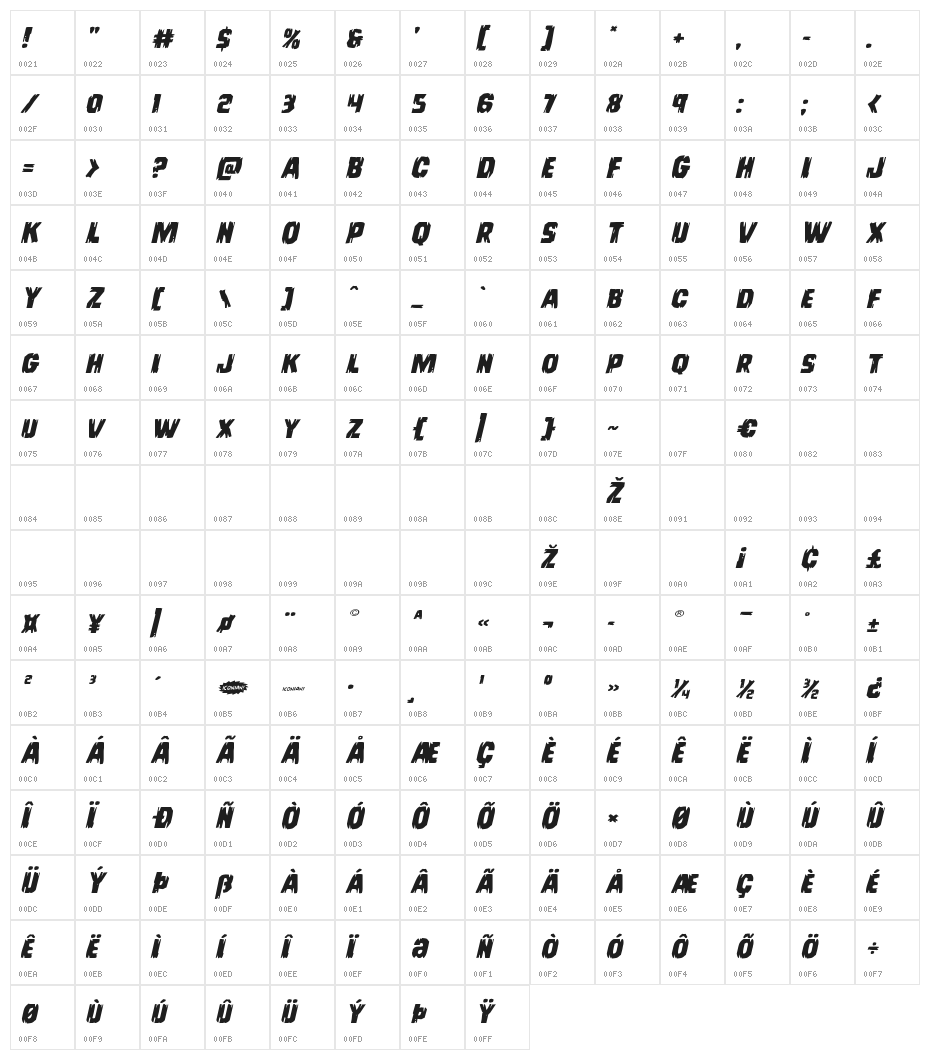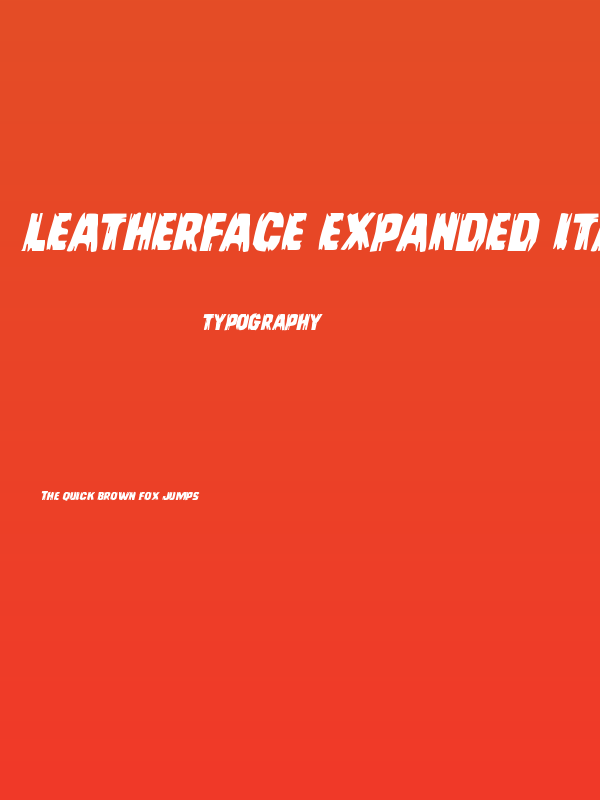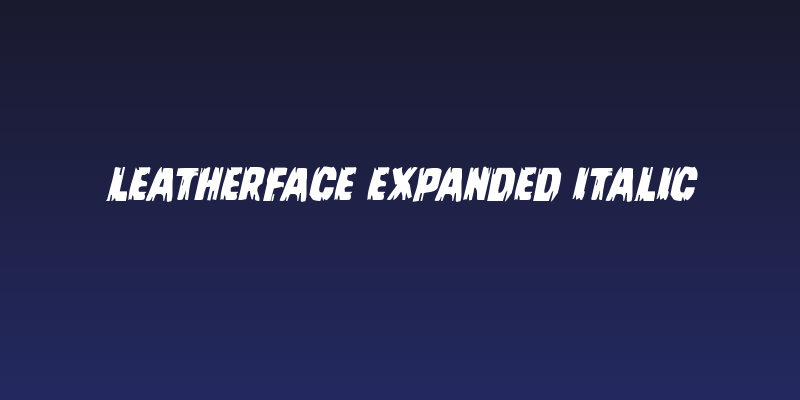
Leatherface Expanded Italic Font
✎ Messy
| Progetti proposti | Ideal for horror-themed designs, movie posters, album covers, and edgy branding projects. |